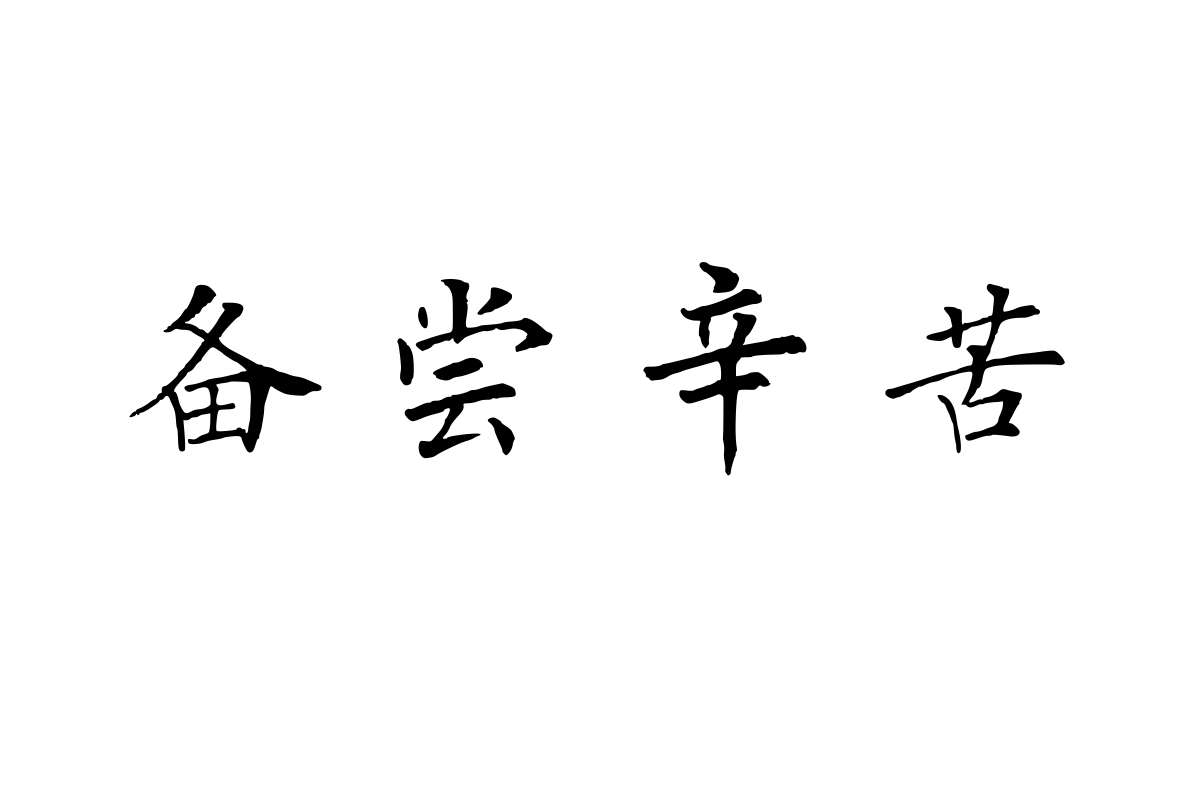
兰米标准楷体简繁版是一款由兰米公司开发的中文字体,它结合了楷书的书写风格和现代设计元素,旨在为用户提供更加舒适、美观的阅读体验。这款字体适用于各种应用场景,如网页设计、广告宣传、书籍出版等。
兰米标准楷体简繁版的字体特点如下:
1. 字形规整:兰米标准楷体简繁版采用传统的楷书字形,笔画清晰,结构严谨,易于识别。
2. 风格独特:这款字体融合了现代设计元素,使得字形更加流畅、优雅。同时,它还保留了楷书中的一些经典元素,如撇、捺、竖弯钩等,使字体更具辨识度。
3. 适应性强:兰米标准楷体简繁版适用于多种字体大小和排版方式,用户可以根据自己的需求进行选择和调整。
总之,兰米标准楷体简繁版是一款功能强大、易于使用的中文字体,适用于各种需要使用中文的场景。